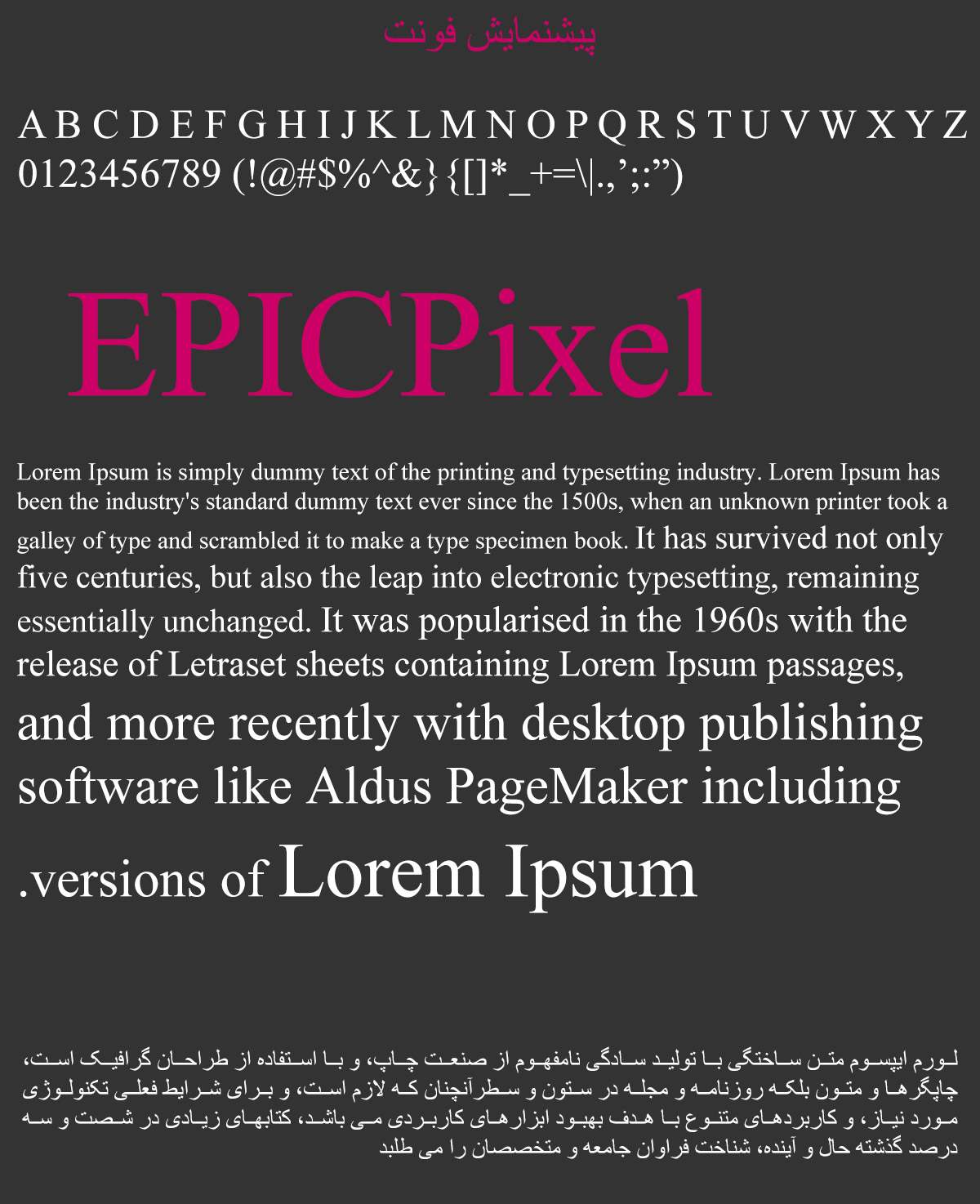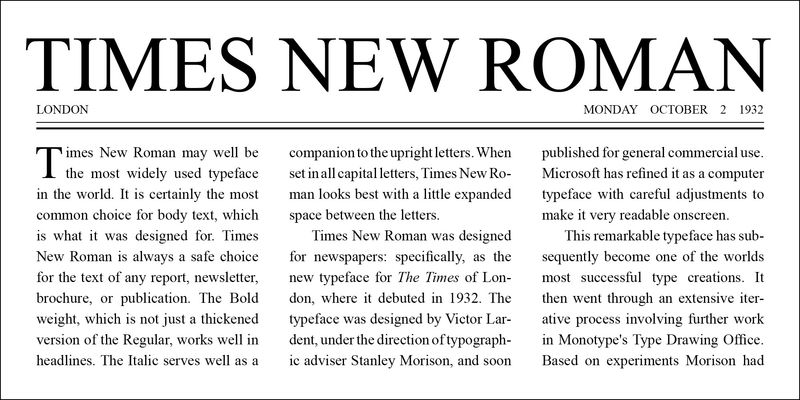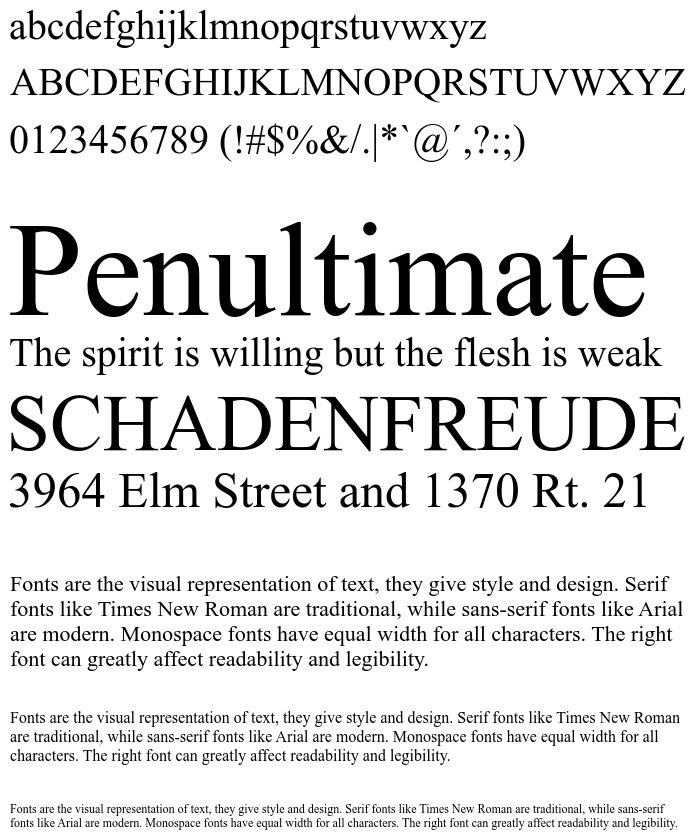
فونت تایمز نیو رومن (Times New Roman)، یک قلم سریف (serif) کلاسیک و رایگان است که در سال ۱۹۳۱ برای روزنامه بریتانیایی “تایمز” طراحی شد. این فونت به یکی از محبوب ترین و پرکاربردترین قلم ها در طول تاریخ تبدیل شده و تقریباً بر روی تمامی رایانه های شخصی نصب است. تایمز نیو رومن با خوانایی بالا و ظاهری مستحکم، برای متون طولانی، اسناد رسمی، گزارش ها و نشریات ایده آل است و وزن ها و استایل های متنوعی را شامل می شود که آن را برای انواع کاربردها مناسب می سازد. این قلم، میراثی از تایپوگرافی قرون ۱۸ و ۱۹ را با رویکردی مدرن ترکیب می کند.
فونت تایمز نیو رومن (Times New Roman)، نامی آشنا برای هر کسی است که با کامپیوتر و نوشتار سر و کار دارد. این قلم سریف که در سال ۱۹۳۱ به سفارش روزنامه بریتانیایی “تایمز” و با نظارت استنلی موریسون (مشاور هنری Monotype) و همکاری ویکتور لاردنت (هنرمند حروف نگاری روزنامه تایمز) طراحی شد، به سرعت به شهرت جهانی دست یافت و امروزه به عنوان یکی از پرنصب ترین فونت ها روی سیستم های عامل شناخته می شود.
ریشه ها و طراحی: ایده اصلی موریسون برای طراحی تایمز نیو رومن، تغییر فونت متن اصلی روزنامه تایمز از یک قلم باریک قرن نوزدهمی به یک طراحی قوی تر و مستحکم تر بود که به سنت های چاپ قرن هجدهم بازمی گشت. او فونت قدیمی Monotype به نام Plantin را به عنوان پایه طراحی پیشنهاد داد. تایمز نیو رومن عمدتاً ابعاد Plantin را حفظ کرد، اما تفاوت اصلی در افزایش کنتراست بین خطوط ضخیم و نازک بود تا تصویری واضح تر و شفاف تر ایجاد شود. این طراحی جدید در تاریخ ۳ اکتبر ۱۹۳۲ برای اولین بار در روزنامه “تایمز” به کار رفت و یک سال بعد برای فروش تجاری منتشر شد. نام “Roman” در “Times New Roman” به سبک عادی یا رومی فونت اشاره دارد که اولین بخش از خانواده تایمز نیو رومن بود که طراحی شد.
تکامل و ویژگی ها: تایمز نیو رومن دارای خوانایی بالایی در صفحات چاپی است و تأثیراتی از چاپ اروپایی اوایل دوره مدرن و باروک را به خود گرفته است. به عنوان یک فونت طراحی شده برای چاپ روزنامه، دارای x-height (ارتفاع حروف کوچک) بالا و descenderهای کوتاه (بخش های پایین رونده حروف) است تا امکان فاصله گذاری خطوط محکم و ظاهری نسبتاً فشرده را فراهم کند. این ویژگی ها آن را برای استفاده در متون طولانی و فشرده بسیار مناسب می سازد. روزنامه تایمز به مدت ۴۰ سال از این فونت اصلی استفاده کرد و پس از آن، به دلیل تکنیک های جدید تولید و تغییر فرمت از قطع بزرگ به قطع روزنامه های کوچک (tabloid) در سال ۲۰۰۴، پنج بار بین سال های ۱۹۷۲ تا ۲۰۰۷ به نسخه های مختلفی از این فونت تغییر داد.
دانلودفونت تایمز نیو رومن شامل وزن های مختلفی است، از جمله Bold (بولد) که فقط یک نسخه ضخیم شده از Regular نیست، بلکه طراحی خاص خود را دارد و برای سرتیترها به خوبی عمل می کند. همچنین Italic (ایتالیک) آن نیز به عنوان مکملی مناسب برای حروف عمودی عمل می کند.
کاربردهای فونت تایمز نیو رومن در طراحی و نشر
فونت تایمز نیو رومن (Times New Roman) به دلیل خوانایی بی نظیر، ظاهر حرفه ای و حضور گسترده در تمامی سیستم های کامپیوتری، به یک انتخاب پیش فرض و بسیار پرکاربرد در حوزه های مختلف نشر، اسناد اداری، دانشگاهی و وب تبدیل شده است. این فونت رایگان و قابل دسترس، برای طیف وسیعی از پروژه ها مناسب است.
کاربردهای اصلی:
- اسناد اداری و رسمی: این فونت انتخاب اول برای گزارش ها، نامه ها، صورت جلسات و تمامی مکاتبات اداری است. ظاهر رسمی و قابل اعتماد آن، به محتوای شما اعتبار می بخشد.
- نشر و چاپ: در کتاب ها، مجلات، روزنامه ها و پایان نامه ها، تایمز نیو رومن به دلیل خوانایی بالا در متون طولانی، گزینه ای بسیار محبوب است. طراحی آن برای چاپ، به آن امکان می دهد تا در اندازه های کوچک نیز وضوح خود را حفظ کند.
- محتوای دانشگاهی: در مقالات علمی، پایان نامه ها، پروپوزال ها و پروژه های دانشجویی، تایمز نیو رومن به دلیل استانداردهای آکادمیک و پذیرش عمومی، انتخاب اصلی محسوب می شود.
- وبسایت ها و وبلاگ ها: برای متون اصلی و مقالات در وبسایت ها و وبلاگ ها که به دنبال خوانایی بالا و ظاهری کلاسیک هستند، این فونت گزینه ای مطمئن است.
- روزنامه ها و نشریات: همانطور که از نامش پیداست، این فونت برای روزنامه ها و نشریات چاپی و دیجیتال طراحی شده و عملکرد بسیار خوبی دارد، به خصوص در بخش های خبری و مقالات تحلیلی.
وزن های مختلف آن، به خصوص Bold و Italic، امکان ایجاد تنوع در سلسله مراتب بصری متن را فراهم می کنند، و آن را برای استفاده در تیترها، تأکید بر کلمات یا جملات خاص و زیرنویس ها نیز مناسب می سازد.